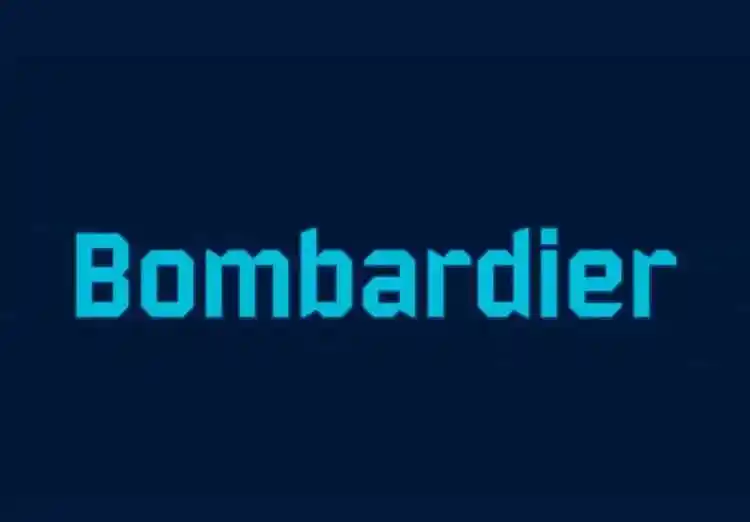
Bombardier Display Font
A Bombardier Display Font é uma tipografia única projetada para destacar textos em grandes tamanhos. Ideal para headlines, logotipos ou qualquer aplicação de display que precise de uma forte impressão visual. Inspirada no jogo Risk of Rain 2, essa fonte apresenta linhas aguçadas e elegantes, projetadas para serem usadas tanto na tipografia tradicional quanto na interface dos usuários digitais. Além disso, a Bombardier Display Font foi ampliada com símbolos do alfabeto cirílico, o que a torna ainda mais versátil. Esta fonte é uma escolha inteligente para quem busca uma solução criativa e inovadora para estilizar qualquer tipo de mídia ou projeto gráfico.